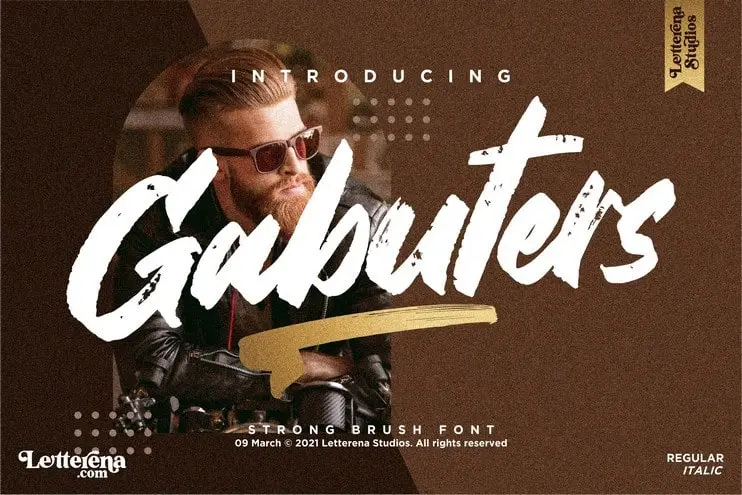
Gabuters Brush Font – Download Grátis
A ‘Gabuters Brush Font’ oferece uma experiência de escrita única, ideal para quem procura estilo e elegância para projetos multimídia. Especialmente criada pela Letterena Studios, essa fonte tem um toque de autenticidade que vem direto da arte manual, perfeita para diversos usos como logomarcas, projetos de marca, designs para móveis de consumo, embalagens de produtos, mugs personalizados, mensagens e cartazes, sacolas de shopping, camisetas, capas de livros, crachás, convites, cartões postais, etiquetas, imagens fotográficas e até mesmo eventos especiais. Seja em qualquer projeto que exija um gosto forte e sofisticado para fazer seu design brilhar ainda mais, a ‘Gabuters Brush Font’ está à sua disposição, garantindo uma qualidade de design impecável para seus trabalhos.